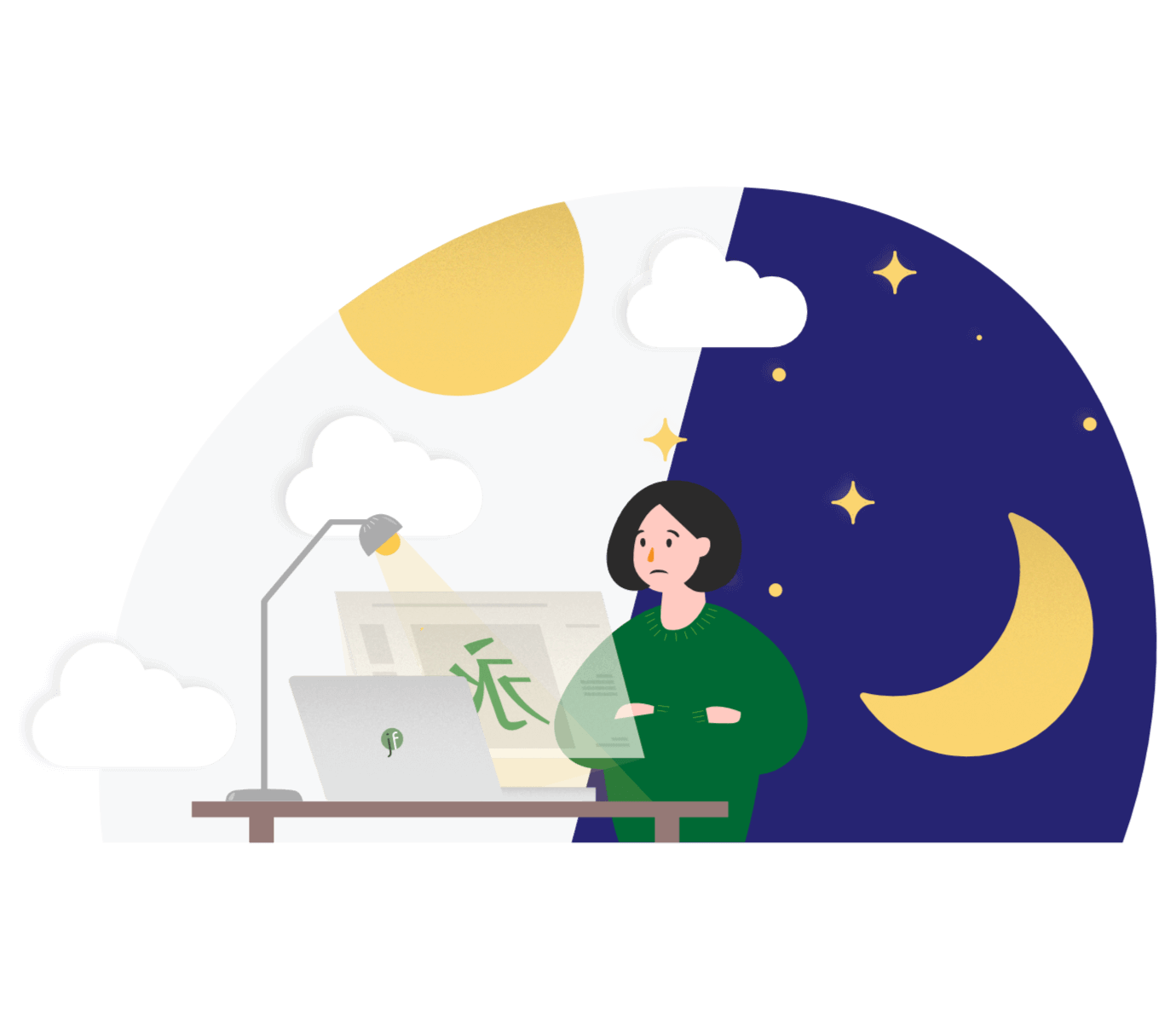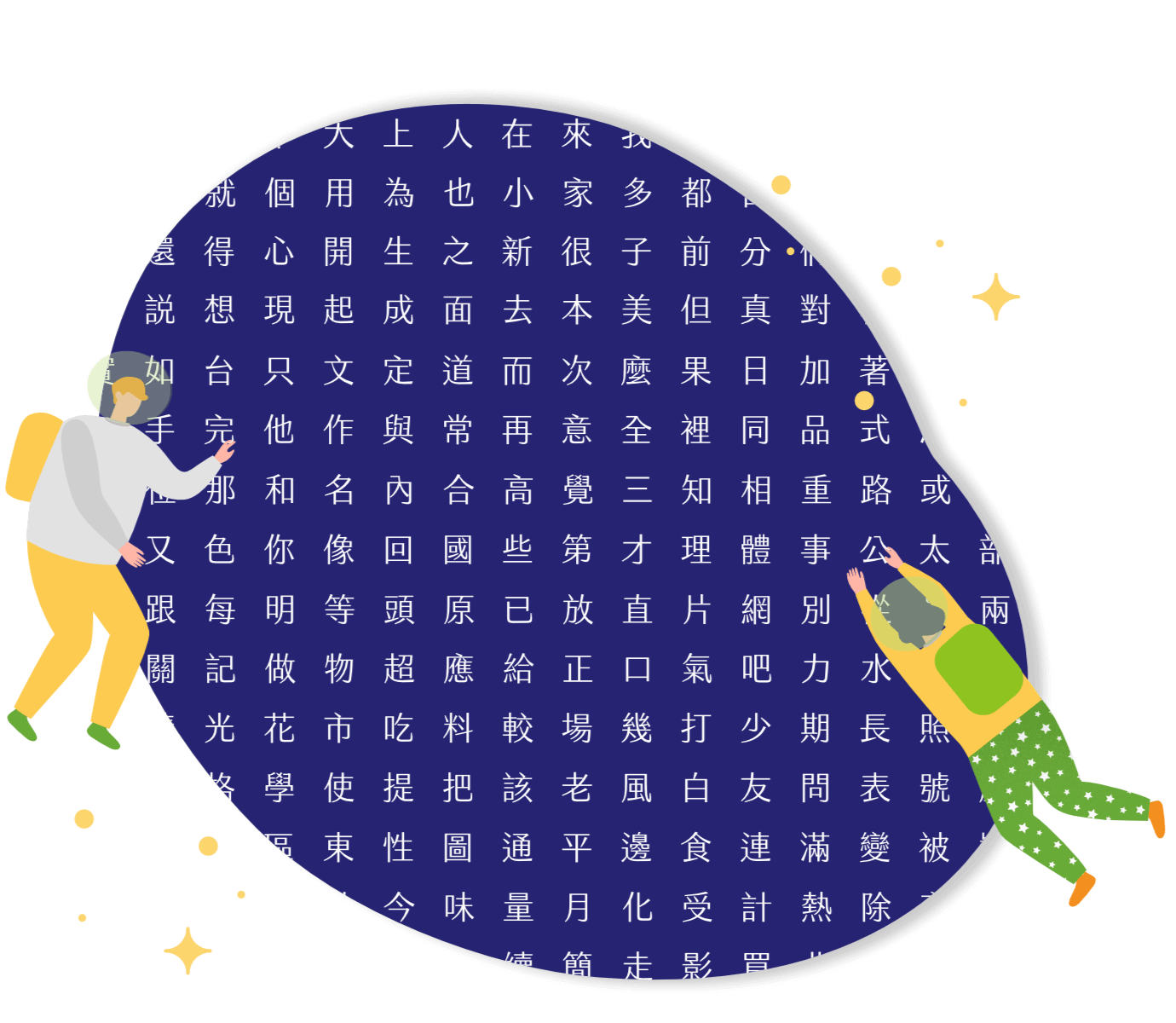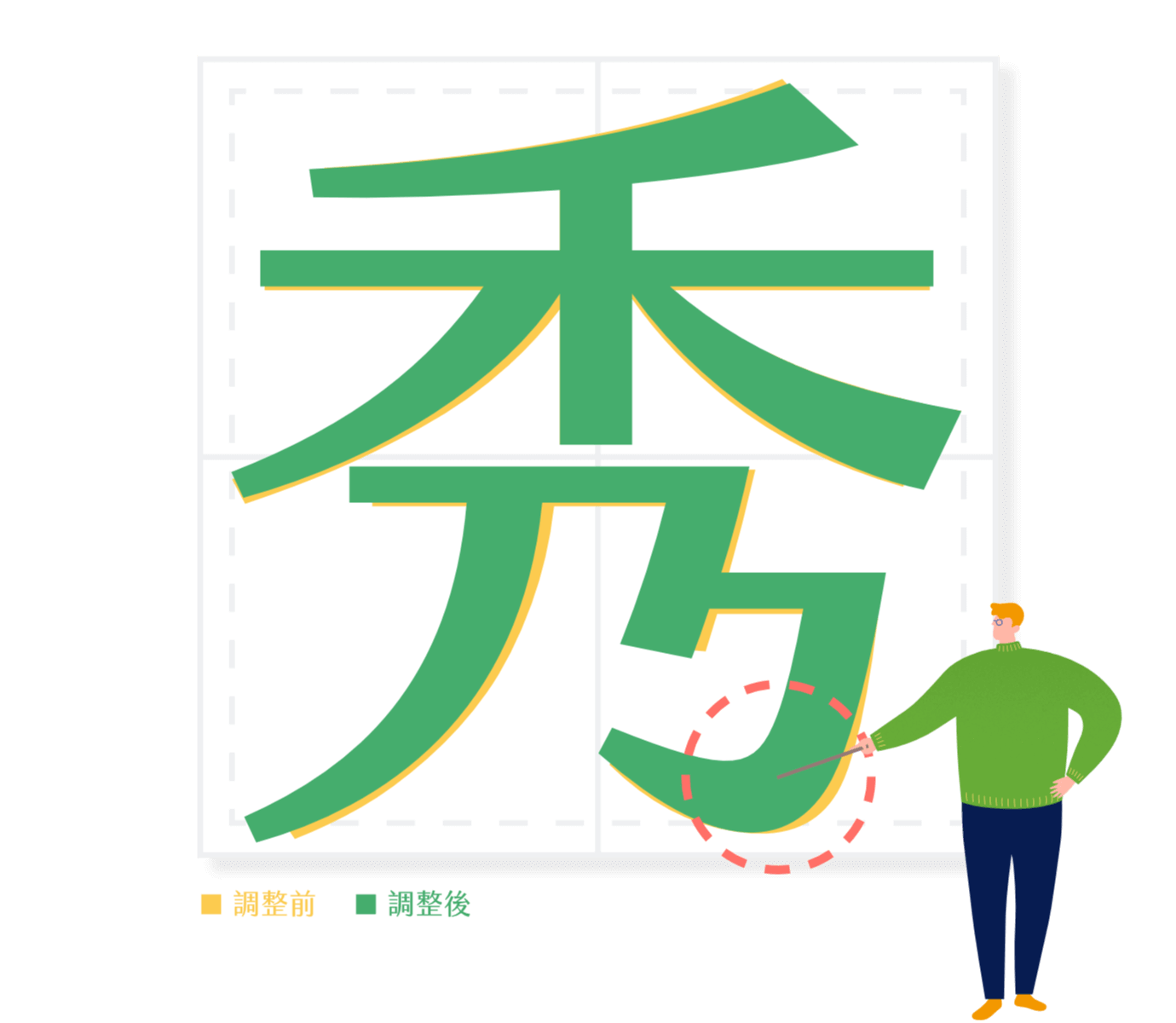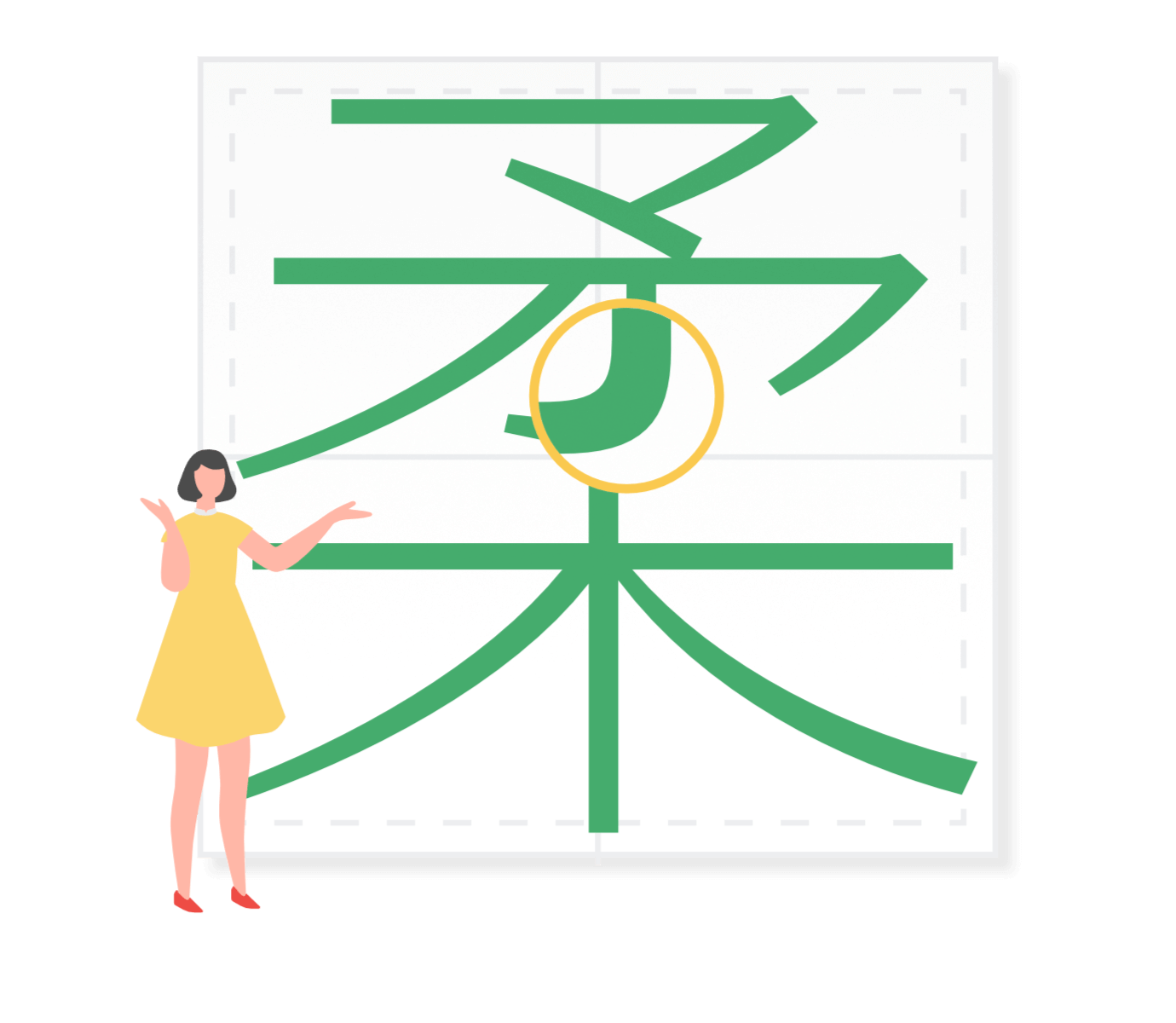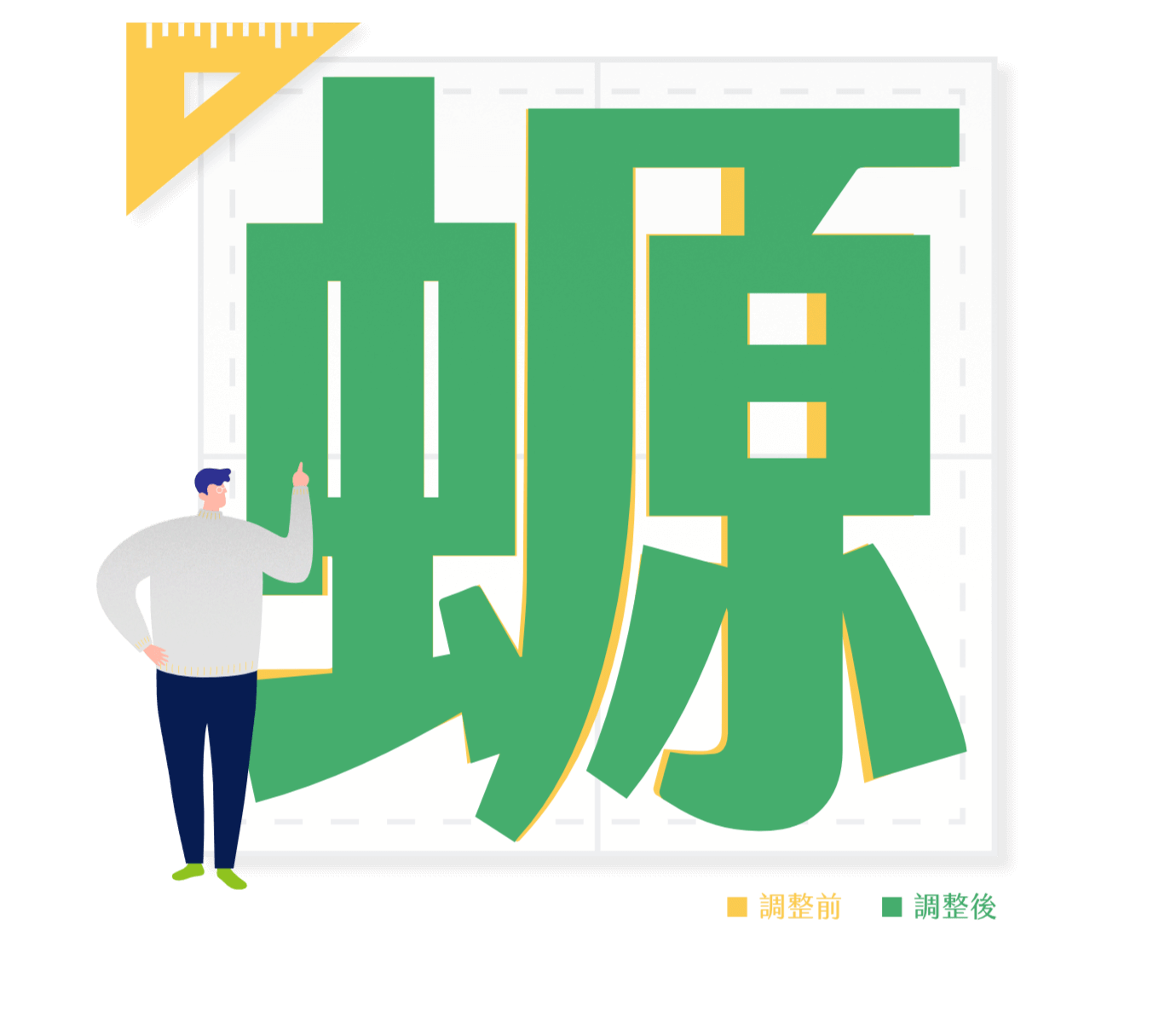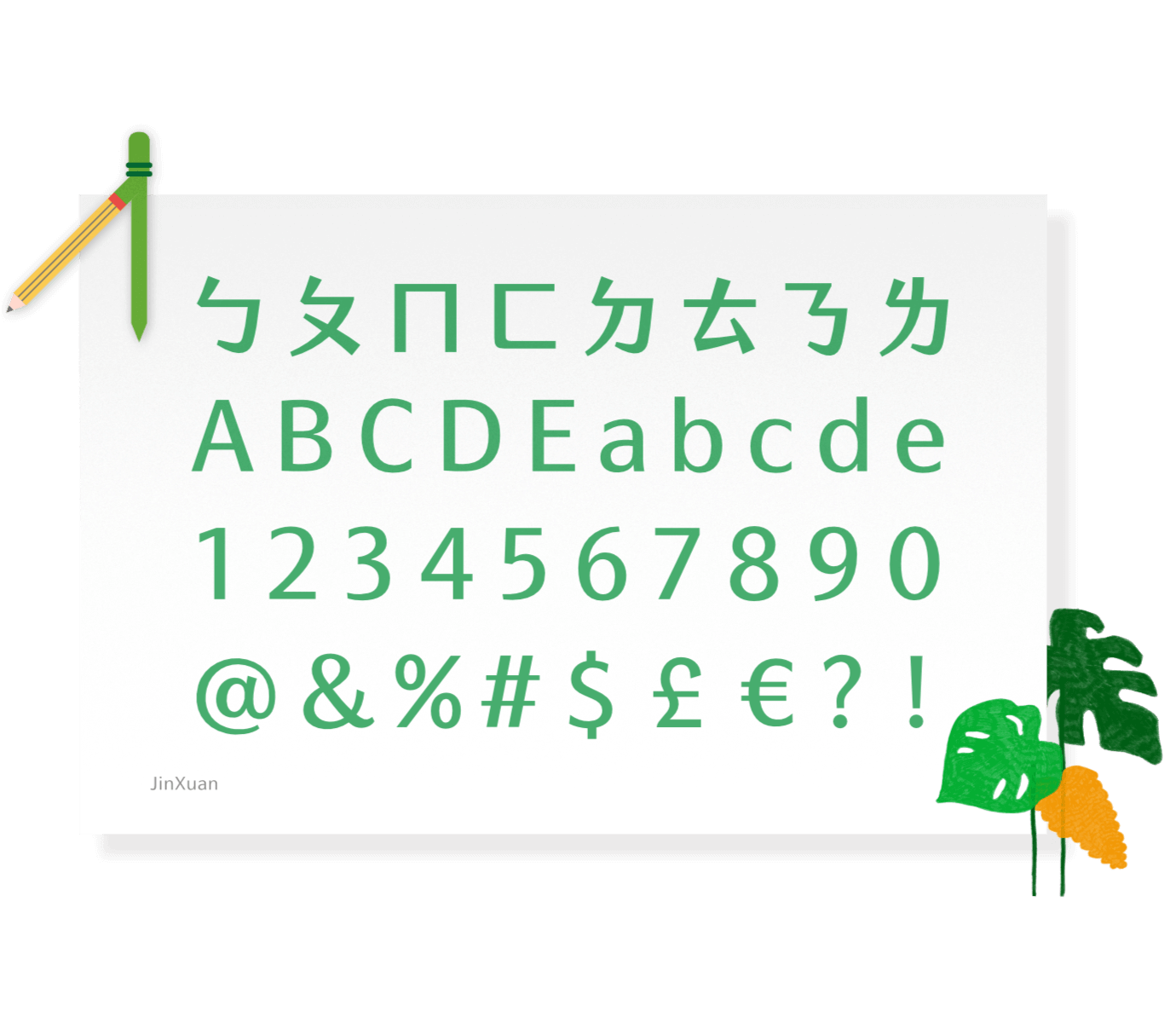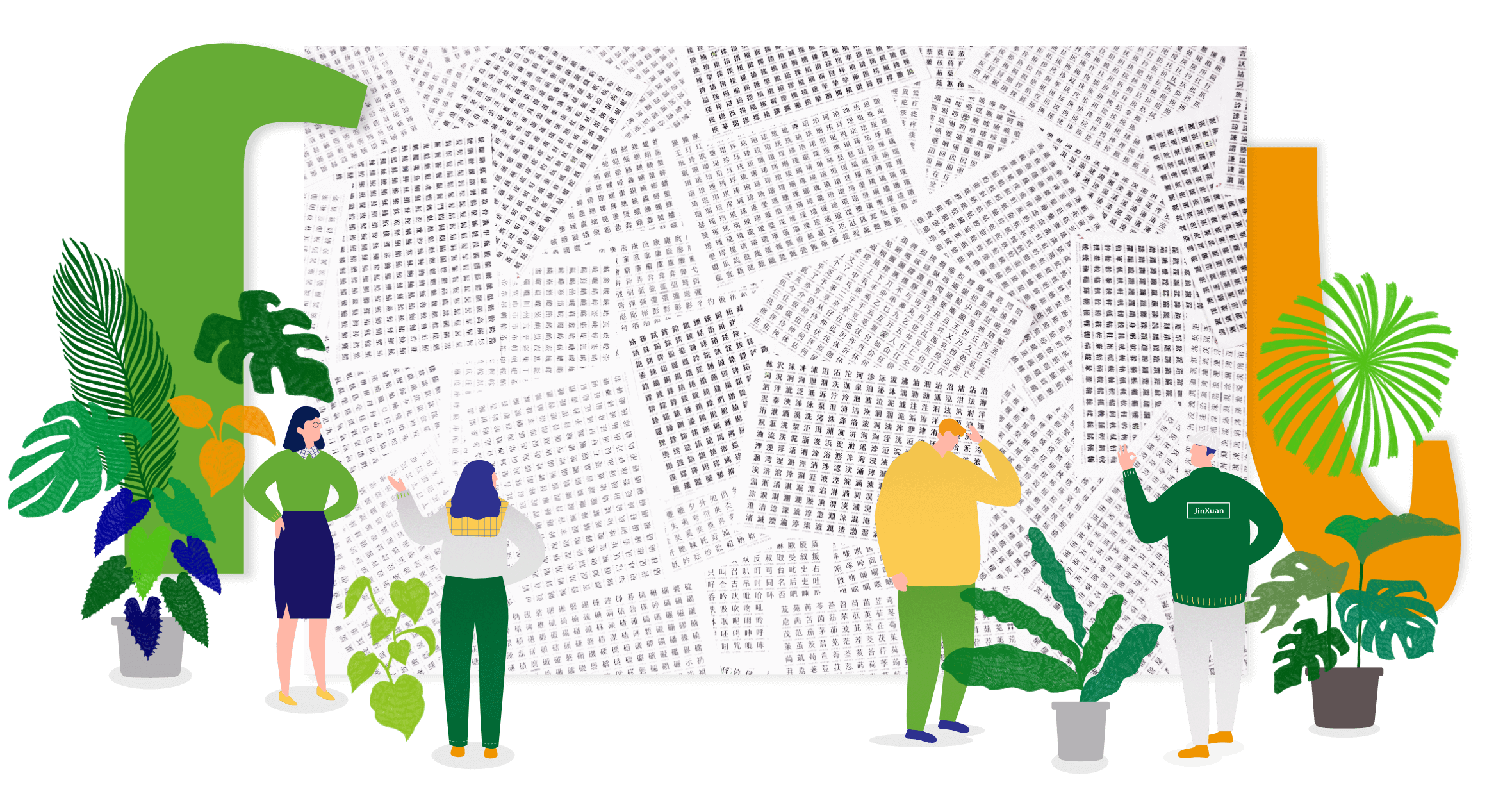
金萱的故事 2
justfont 團隊過去四年做的事情。
不只是技藝的考驗,
也是對心智、體力的考驗。
雖然電腦科技已經很先進,但面對動輒上萬字的作業量,還要達到每個字精密的
視覺平衡,還是只能仰賴設計師眼到、心到、手到,一筆一筆設計出來。
痛苦的過程
募資之後,面對短短一年的交貨期限,每天都有規定完成字數,但字體風格到此還沒有完全定型,原本以實習身份參與計畫的五位設計師因為生涯規劃相繼離開,在距離交貨僅剩六個月的時間。團隊只能緊急招募字型設計師,從頭開始。這段期間,字型設計重擔幾乎都落在總監霞姐的身上,幾次還因眼壓過高,影響視力。
重新規劃
重新招募新的設計師加入後,仍要從基本的 300 字重新開始並學習曲線的設計,一邊面臨著越來越緊迫的交貨期限,一邊拿捏美感,觀察構成金萱風格的基本規則,在「金萱半糖」製作後期,曲線樣式需要經過重新審查、修整。
回到那個在涼麵攤開會的夏日中午。雖然設計師們同心協力在 2016 年準時完成了金萱半糖,但設計「內文」應用的微糖,又面臨新的挑戰。比方說,為了閱讀,必須降低對眼睛的刺激。本來的勾筆過於彎曲、上揚,這些地方存在感太強,不利於長篇閱讀。所以在設計金萱微糖時,必須回頭修改金萱半糖的樣式。
金萱微糖
用心雕琢細膩曲線
極細字體,幾乎沒有豐滿的「肉」與其它元素,所以骨架均衡、曲線優美,更會被放大檢視。每天盯著字,越是深入用心的製作,越能感受到心目中的金萱是溫柔、細膩的字體,所以將細微的曲線變化視為非常重要的美感根源。
金萱全糖
爭取清晰「白空間」
對粗體字而言,最缺乏的是白色空間。白色空間,是令字體清晰的關鍵。設計師們不得不施展視覺的幻術:巧妙縮小某些筆畫、改變部件擺位,甚至改了某些細微的造型,使他們騰出更多呼吸的空間。
符號、歐文、數字⋯
一個都不能少
對金萱設計團隊來說,歐文、數字、符號與漢字的完成度同等重要。因為字型最大的任務在於構成整體版面,只有漢字好看是不夠的。所以都會邀請相關排版專業的朋友、設計師,針對混合排版、符號位置、間距⋯等議題,一同把關品質。
就這樣,盡心盡力的製作,中途也有很多朋友支持、鼓勵、幫忙。終於,在2018年底,完成了金萱全系列。
這些就是justfont字型設計團隊過去三年做的事情。不只是對技藝的考驗,也是對心智、體力的考驗。想到這裡,眼框濕潤,分不清是淚水,還是剛剛點的眼藥水。(藍光傷眼,眼睛保健很重要,葉黃素請業配)
最終出貨之前,看著我們的孩子,五味雜陳。每一筆都想照顧到無微不至,希望它們以最完美的姿態登台演出。但時間到了,只能放手,讓它們去盡力活出自己的生命。請大家盡量關照,讓它們順著你的意思表演吧!精心設計的字體,希望你會喜歡。我們也會永遠以它們為傲。